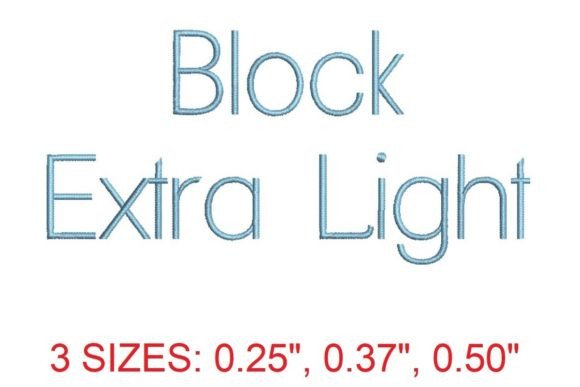
Block Extra Light Embroidery Font
De Block Extra Light Embroidery Font is een elegante en minimalistische lettertypeoptie die perfect past in het segment van eenvoud. Met zijn lichte, fijne lijnen creëert deze font een schone, moderne look die ideaal is voor projecten waarin subtiliteit en finesse centraal staan. Of u nu bezig bent met het ontwerpen van een uniek logo, personaliseerde cadeaus of zelfs een bescheiden decoratief element, de Block Extra Light Embroidery Font biedt een ongeëvenaarde combinatie van stijl en functionaliteit.
Bouwkwaliteit en technische details
Wat betreft specificaties, is de Block Extra Light Embroidery Font ontworpen om zowel in kleine als grote formaten uit te blinken. Het gebruik van dunne, consistente lijnen maakt het mogelijk om gedetailleerde patronen te creëren zonder dat het ontwerp overweldigend wordt. De kwaliteit van het rasterwerk is indrukwekkend, wat resulteert in scherpe, duidelijke letters die ook na herhaaldelijk wassen en dragen hun vorm behouden. Bovendien is dit lettertype geoptimaliseerd voor verschillende soorten textiel, waardoor het toegankelijk is voor zowel beginners als ervaren borduurders.
Voor wie is dit product het beste?
Deze font is vooral geschikt voor creatieve individuen die op zoek zijn naar een eenvoudig, maar krachtig design. Het is perfect voor handelaren, kleine bedrijven, en hobbyisten die willen dat hun producten een professionele, maar verfijnde touch hebben. Van t-shirts en hoeden tot zakdoeken en tafelkleden, de Block Extra Light Embroidery Font past zich aan bij een breed scala aan projecten en stijlen. Het is ook een uitstekende keuze voor mensen die een minimalistisch thema willen toepassen in hun dagelijkse accessoires of huisdecoratie.
Een praktisch tip: Combineer de Block Extra Light Embroidery Font met een iets donkerder of dikker lettertype om tekstuele contrasten te creëren, wat kan helpen bij het leesbaarheid en visuele aantrekkelijkheid te vergroten.
Hoe het zich verhoudt tot de concurrentie
In vergelijking met andere embroidery fonts, zoals de Bold Sans Serif of de Classic Script, staat de Block Extra Light Embroidery Font uit door zijn lichtere, meer discrete aanpak. Terwijl bolder en script-stijlen vaak meer nadruk leggen op expressiviteit en dramatiek, biedt de Block Extra Light een subtiele elegantie die perfect is voor designs waarin minder meer is. Voor projecten die een minimalistische en moderne sfeer nastreven, is deze font een uitmuntende keuze.